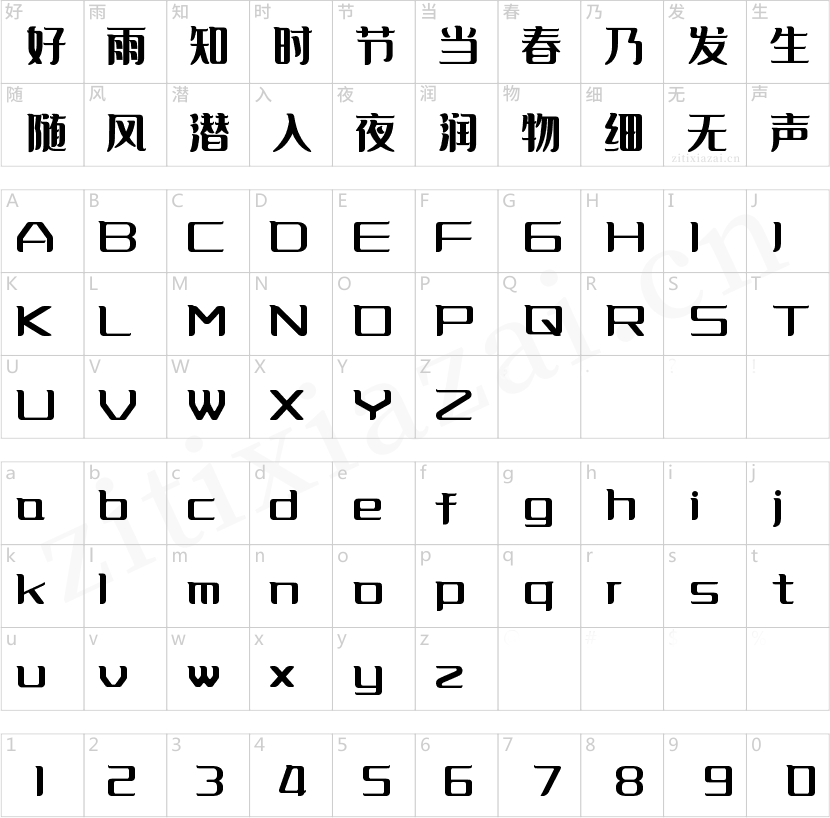
字魂银翼创世黑
字魂银翼创世黑,这款字体结构工整、笔画清晰,兼顾美观与易读性,适用于标题、正文、海报、包装、LOGO 等多种场景。字形优雅稳定,风格百搭耐看,适配日常排版与创意设计,让文字呈现更舒适、更具质感。字魂银翼创世黑一笔一画,皆是细节,以均衡的比例、流畅的线条打造舒适视觉体验,字形端正大气,风格简约现代。无论是商业设计、品牌宣传还是日常排版,都能轻松驾驭,让文字更有格调与力量。字魂银翼创世黑字体下载。